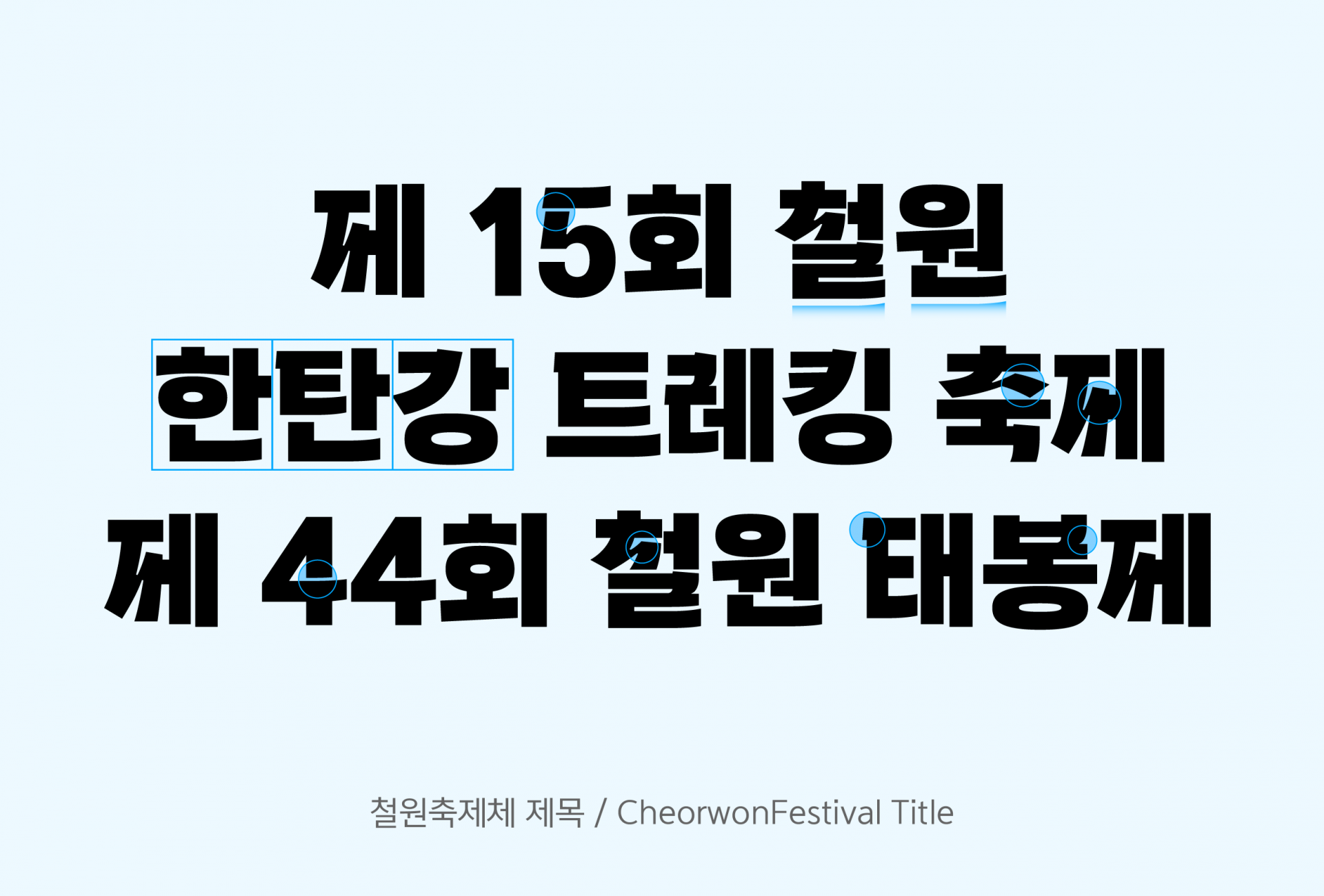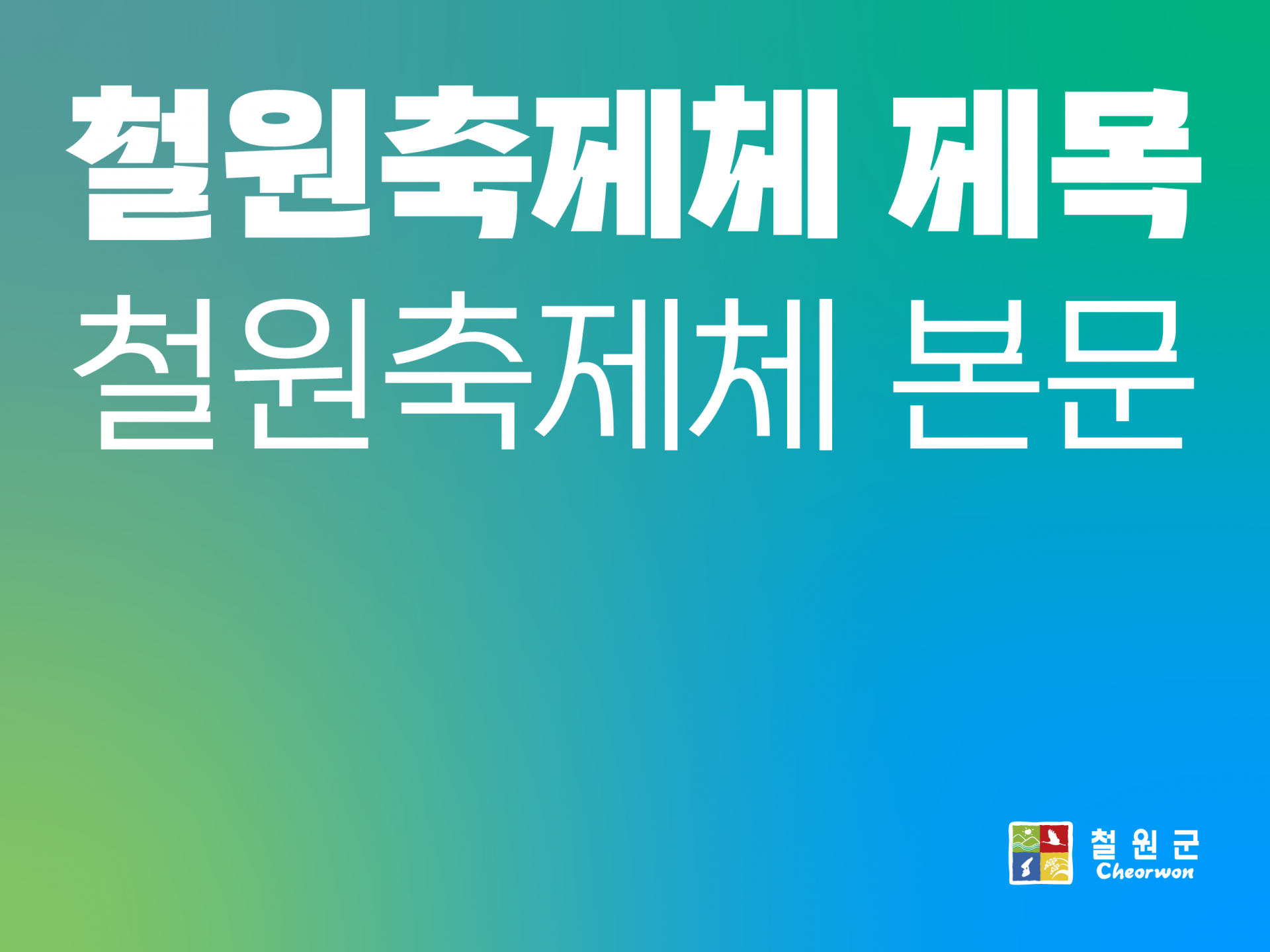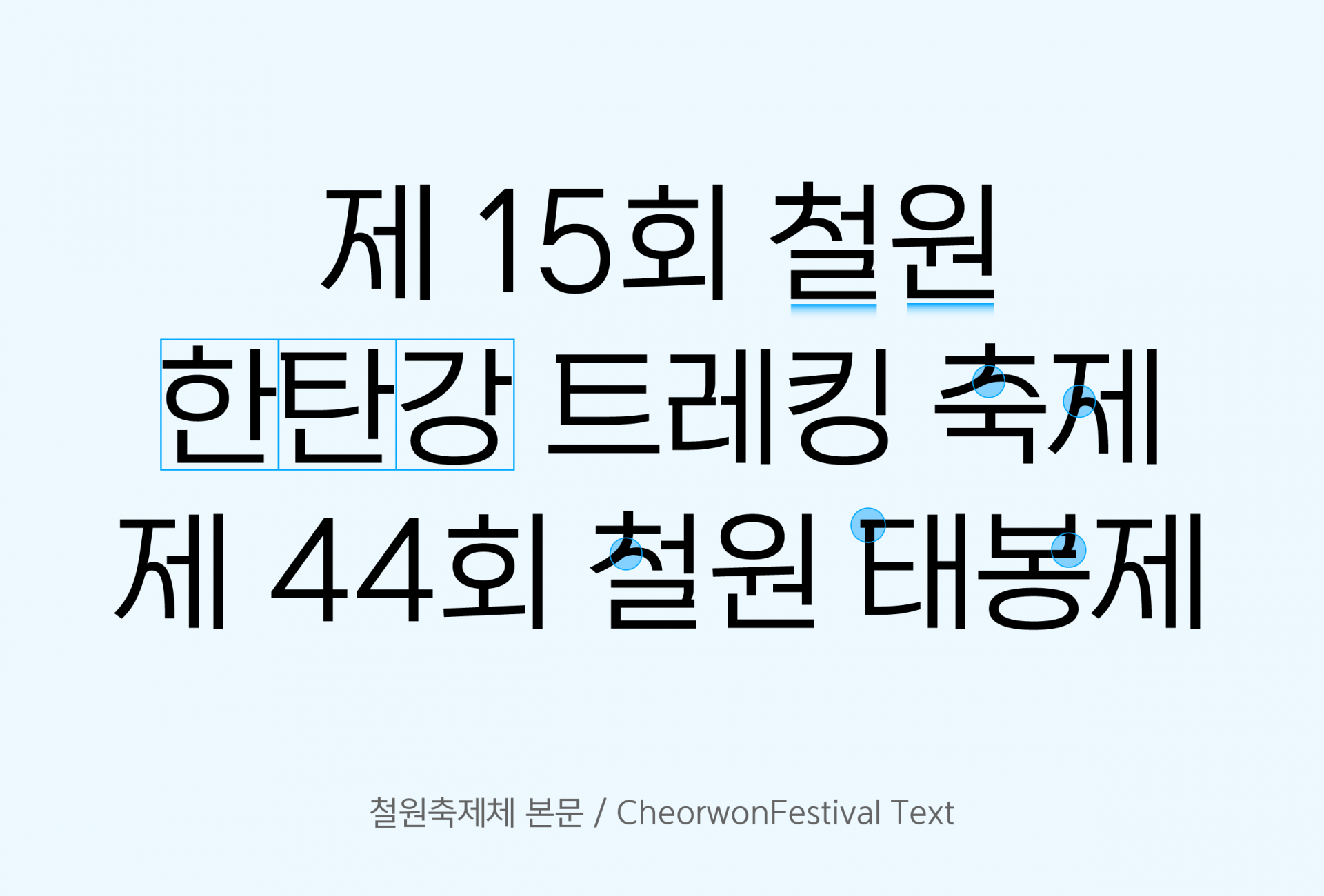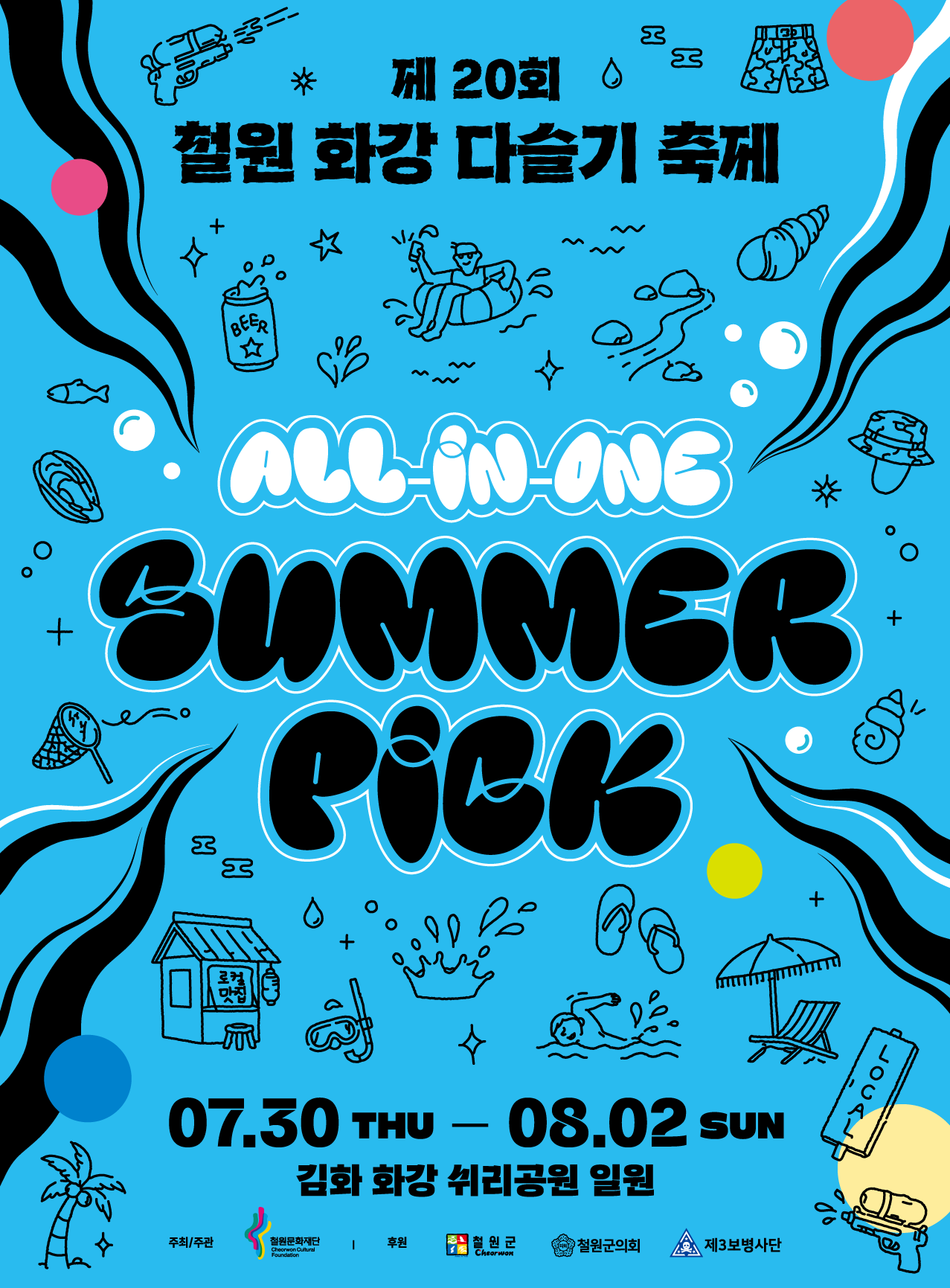
철원군 [철원축제체 제목, 본문]
철원군 축제 브랜드 서체는 시선을 사로잡는 강렬한 인상과 정보 전달의 가독성을 동시에 확보합니다. 철원의 지리적 특징과 문화적 자산을 조형에 반영해 지역 고유의 브랜드 아이덴티티를 시각화했습니다. 분단을 넘어선 평화와 화합, 페스티벌의 경쾌한 기타 선율과 관객의 열정을 리드미컬한 자소 형태로 담아냈습니다.